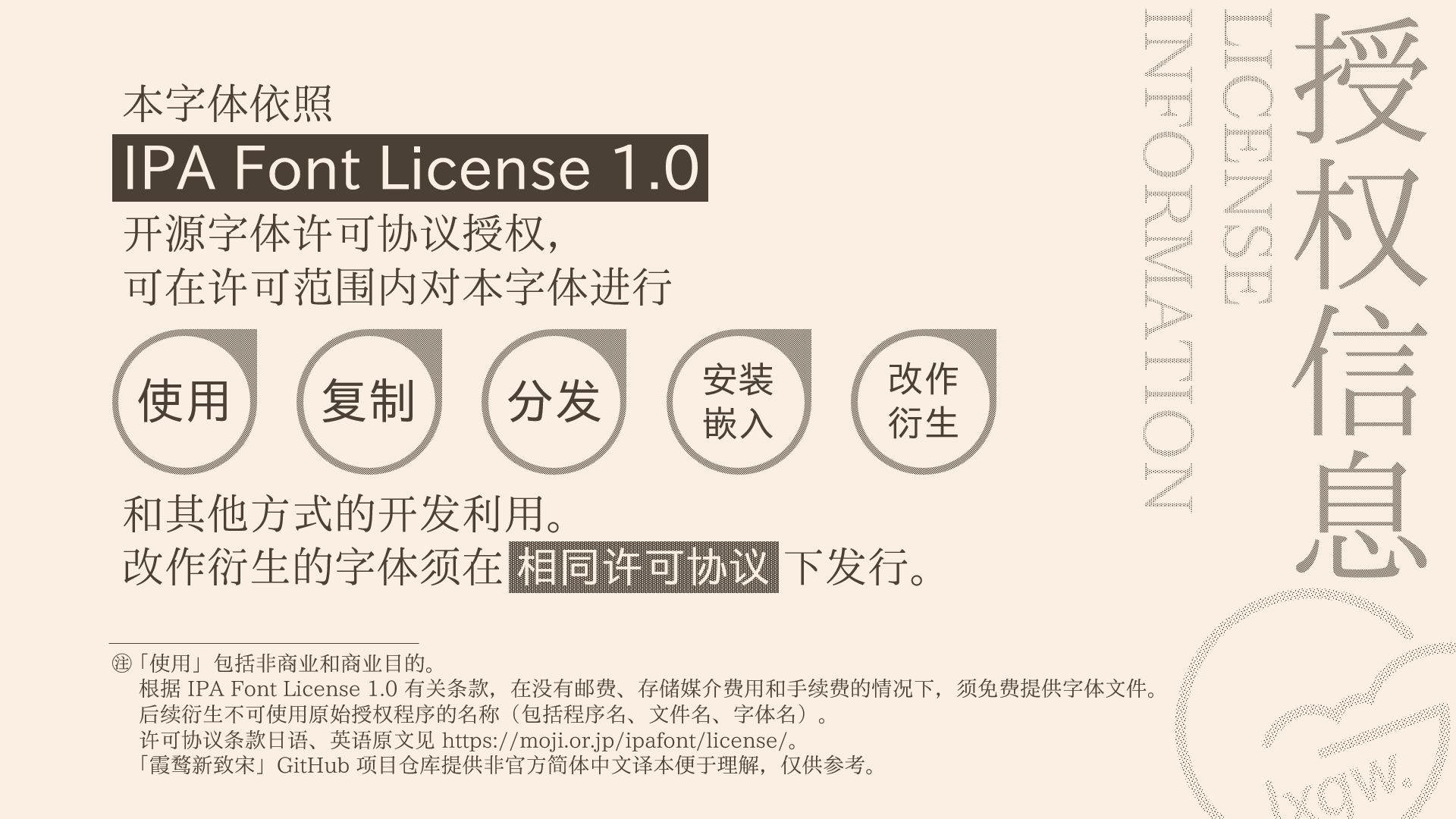
霞鹜铭心宋是在日文字体 「こころ明朝体」的基础上修改制作的一款中文免费宋体字体,将霞鹜新致宋(LXGW Neo ZhiSong)字面横向压缩 85%,并增加圆角,更加清瘦、圆润。
目前包含 GB/T 2312-1980 一级字、《通用规范汉字表》一级字、《现代汉语常用字表》 3500 字。
注:霞鹜铭心宋(LXGWHeartSerifCHS)所收字符相比于新致宋会有所欠缺。